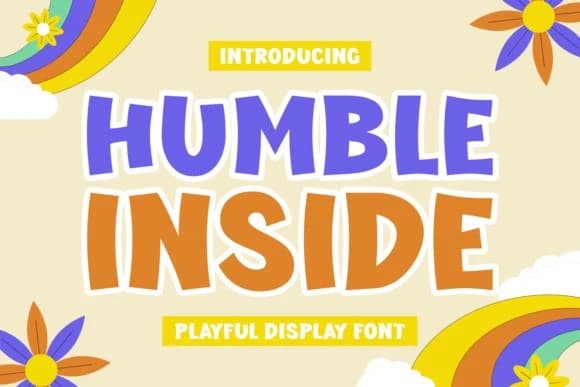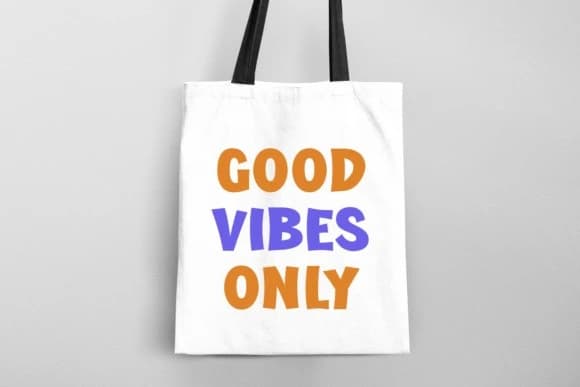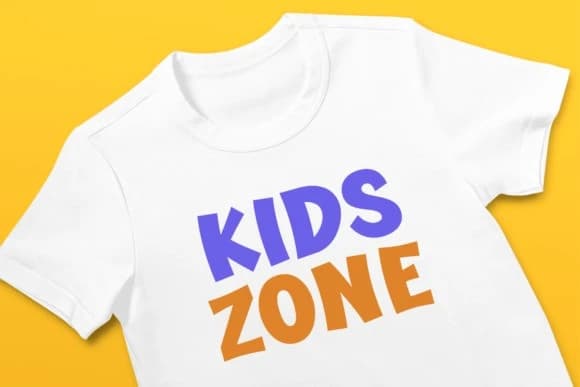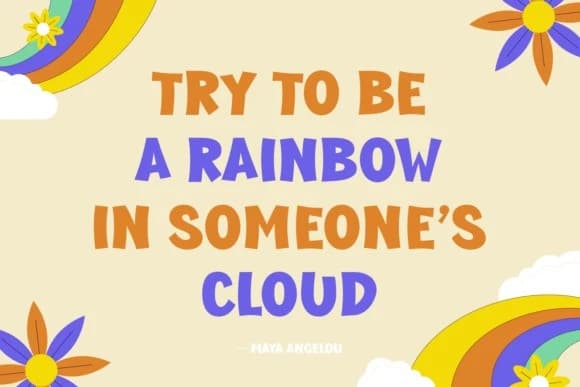
Humble Inside Font
Humble Inside Font, sevgi ve sadelik yayan çok yönlü bir gösterim yazı tipidir. Bu ustaca yazı tipi, masumiyet duygusunu modern bir zarafetle sorunusuz bir şekilde birleştiriyor ve çocuk projeleri için mükemmel kılıyor; okul baskılarından eğlenceli çizgi film tasarımlarına kadar geniş bir kullanım a
Humble Inside Font, sevgi ve sadeliği yayan çok yönlü bir gösteri yazı tipidir. Bu ustaca tasarlanmış font, masumiyet duygusunu modern bir hava ile sorunsuzca birleştirir ve çocuk projeleri için mükemmel hale getirir; okul baskılarından oyuncu karikatür tasarımlarına kadar.